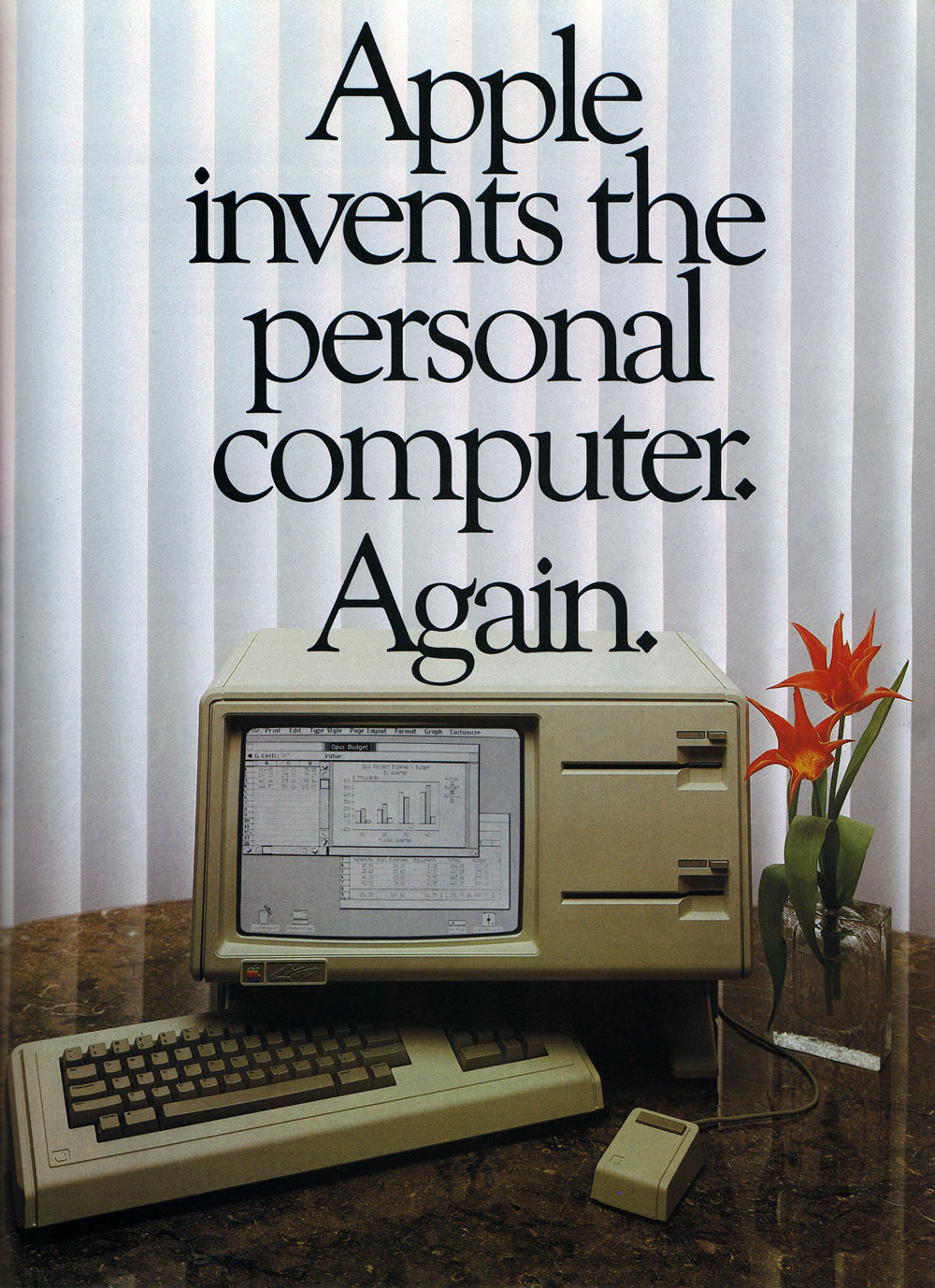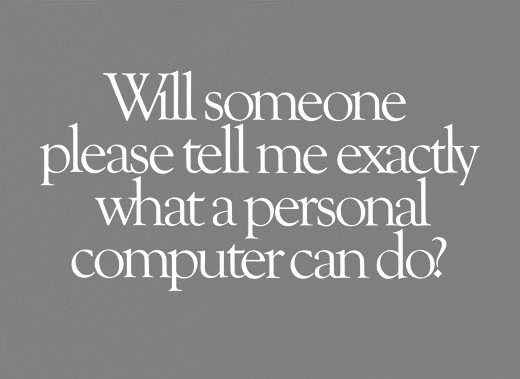
Schrift aus Apple-Werbung 80er Jahre
Naja, die von Apple verwandte ITC Garamond wurde ja auch noch (exklusiv?) überarbeitet (Bitstream glaub ich).
Ist das Bild überhaupt von Apple selbst?